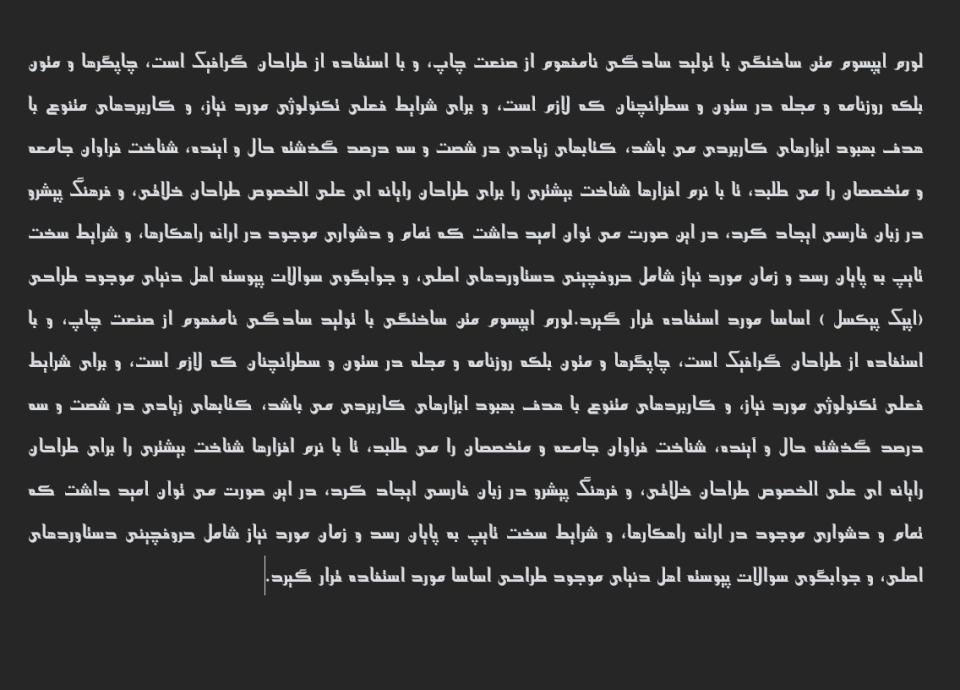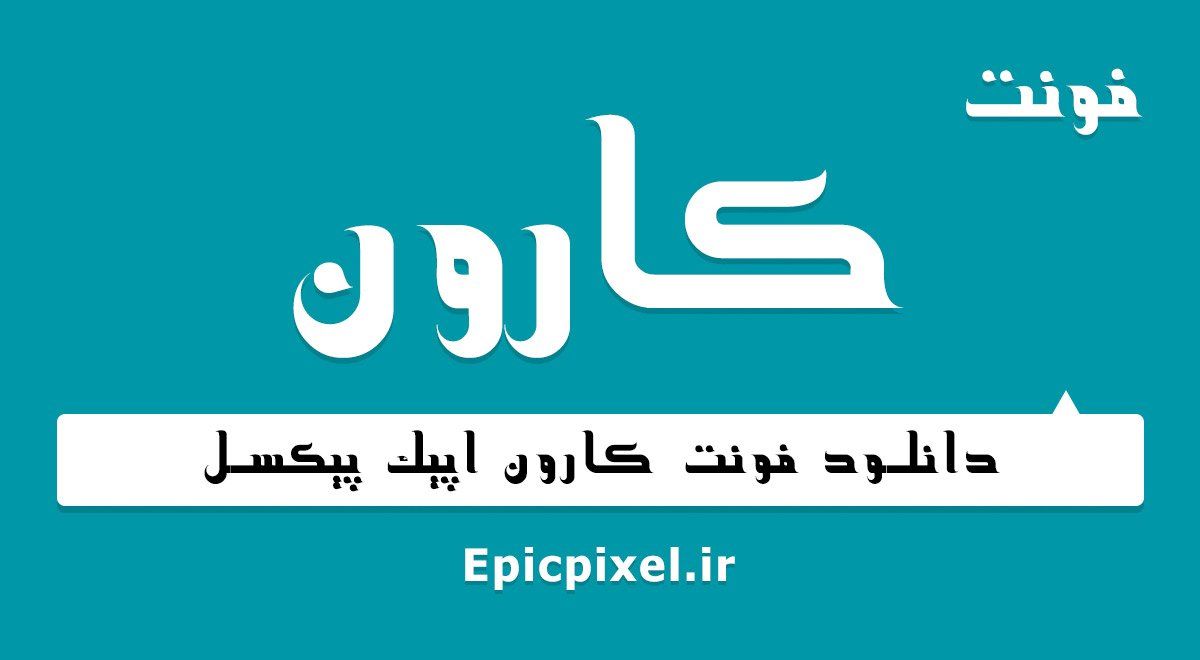
فونت کارون فارسی با طراحی زیبا و خلاقانه، ترکیبی منحصربه فرد از سنت و مدرنیته را به ارمغان می آورد. یکی از ویژگی های برجسته این فونت، خوانایی بالای آن در اندازه های مختلف است که باعث می شود متون شما به راحتی قابل خواندن باشند.
همچنین، کارون با رعایت استانداردهای تایپوگرافی، به شما امکان می دهد که متونی زیبا و جذاب داشته باشید. این فونت به صورت رایگان عرضه می شود و استفاده از آن در پروژه های مختلف بسیار آسان است. هرچند باید توجه داشت که در برخی موارد، ممکن است حروف کوچک در اندازه های بسیار ریز کمی دشوار خوانده شوند. اما این نکته کوچک نمی تواند از جذابیت و کاربردی بودن این فونت بکاهد.